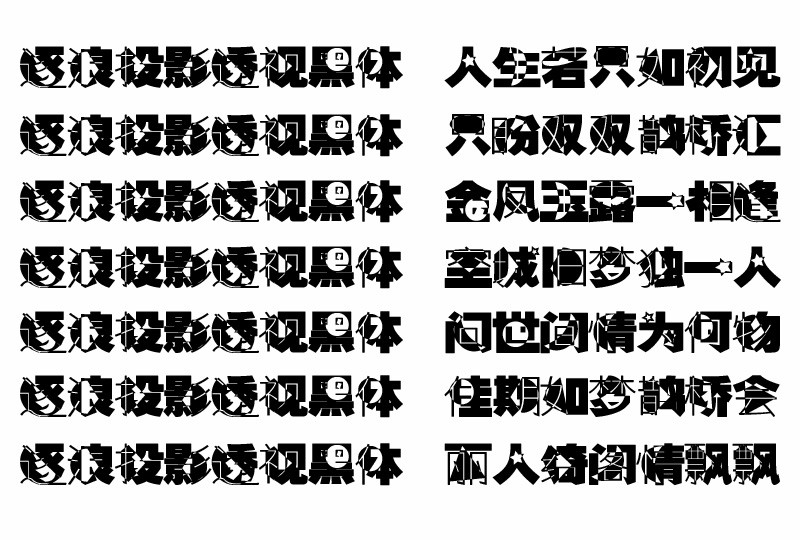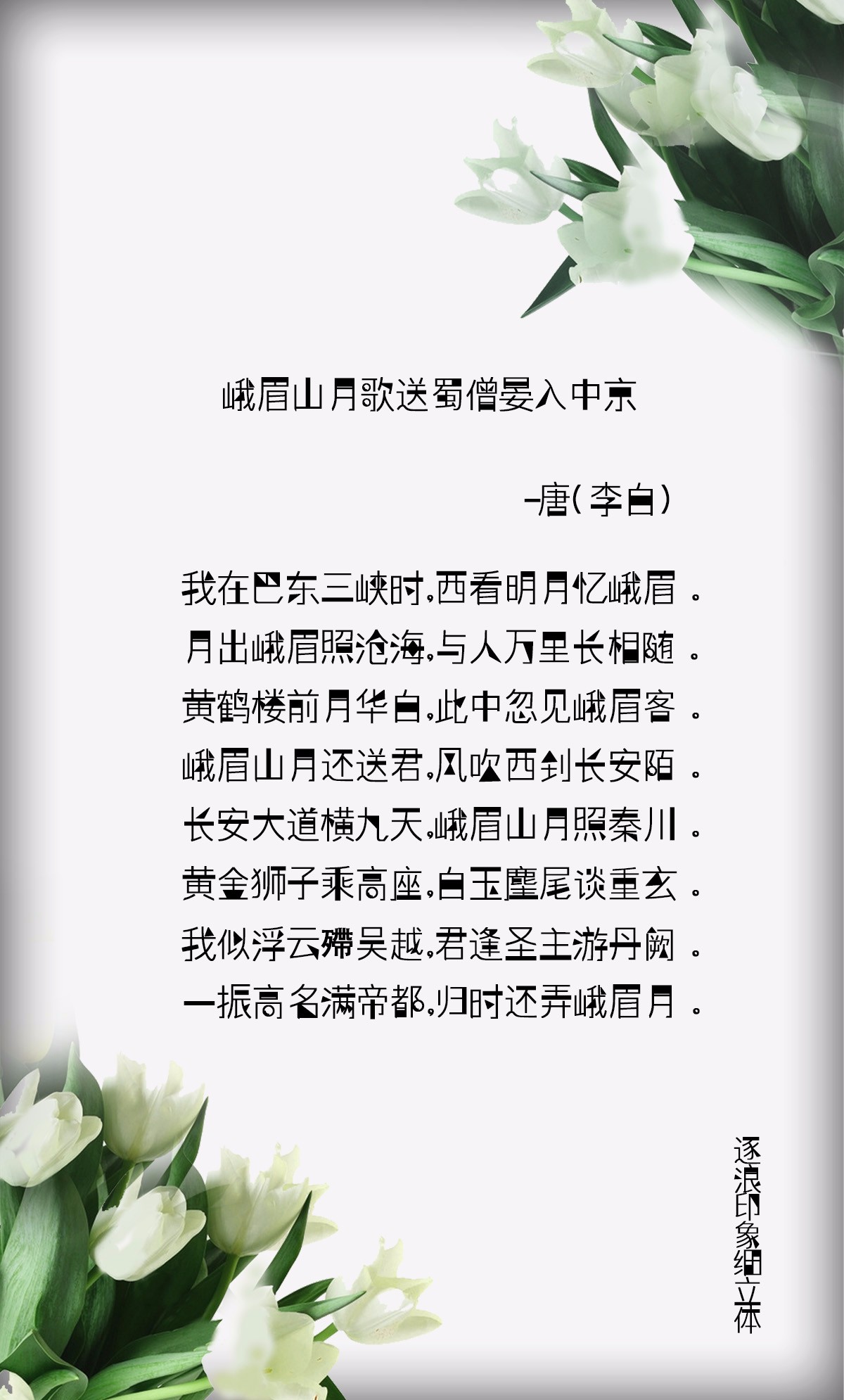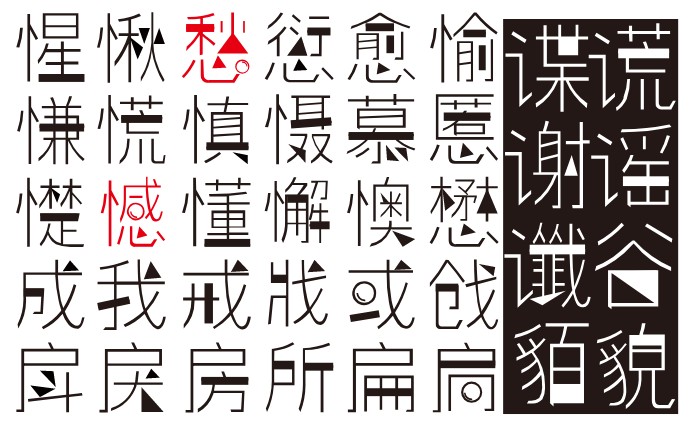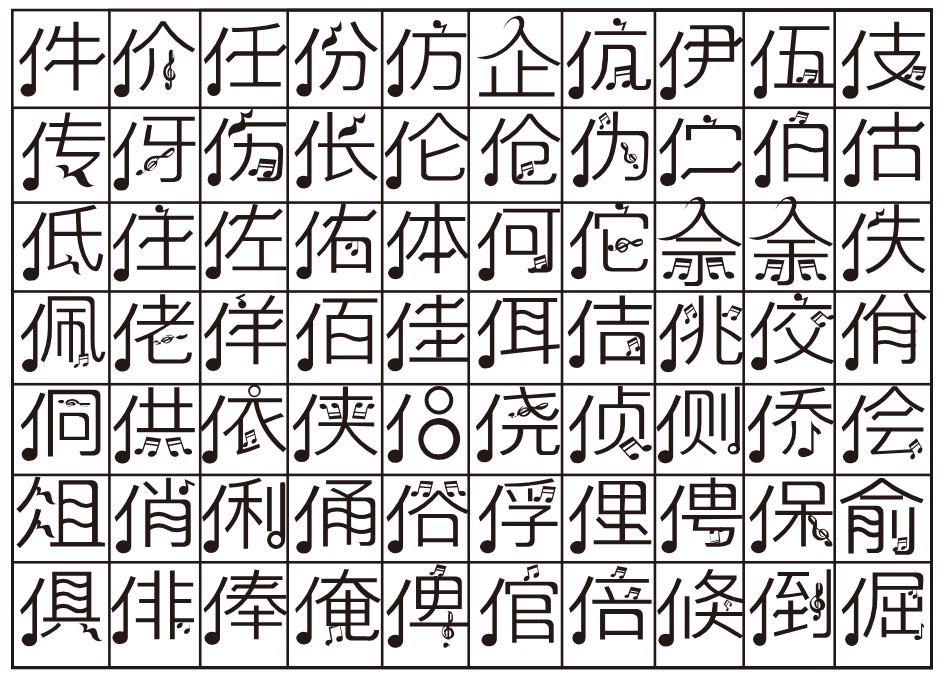
大美汉字-逐浪字库发布2018度中期作品
2018年5月,逐浪字库迎来了新的一期字体更新,这次的产品结合了多方面发效应,此次字体的更新也是相当迅速的,对于开发者及字体设计爱好者来说的话,已经是等待的有点迫不及待了,这次更新的字体是有着根据现代人与结合古代人对字体这块的认知来更新的,为了能做设计出这次的字体,也是经过了多方面的更新与设计,本次逐浪字库发布的四款字体分别为:逐浪投影透视黑体、逐浪印象细立体、逐浪帅宋斜楷体、逐浪音乐符号歌谱体。
针对于这次的更新我们的字库设计部分也是用了很大的准备来创作的,空间跨度很大,其中逐浪印象细立体这款字体的立体主义(Cubism)是西方现代艺术史上的一个运动和流派,又译为立方主义,1908年始于法国。立体主义的艺术家追求碎裂、解析、重新组合的形式,形成分离的画面,以许多组合的碎片型态为艺术家们所要展现的目标。艺术家以许多的角度来描写对象物,将其置于同一个画面之中,以此来表达对象物最为完整的形象。
逐浪字库的团队成员,以印象主义切入,创造了独到的字库体验。
它如三角台灯,照亮下面的丽人、生活与家。如字:流、琦
它如远方的山,又如父爱如山,在字的中间形成重心,如字:离
它是实验室的小烧瓶,俏皮的液体在不断上升-如字:潮。
它是方正厚实的几何之美,值得信任-如字:屋。
它有着红黑与、方与圆的对比-如字:蹦。
它向不规划挑战-如字:依、新、柳
它能在压抑的类比中脱颖而出-如字:熙。
它比别人更加多姿多彩,却又无感累赘-如字:柳
它如同绅士,总是身边有丽人或是配合得体-如字:酥
它如同毕加索笔下的几何造型,虽然看似简单,却又别具风格。
看似堆砌,却又有几何之美。
将西方的几何美学与东方的立体造型结合,
创造出独特的美,
使书写的意境得到最大的化进升。
逐浪印象细立体欣赏:
说完了逐浪印象细立体,再来说说看我们的逐浪音乐符号歌谱体吧,这款字体唯一特色的一点是体现出了音乐的风格,特别像是有些做广告牌的,又或者是传媒公司都可以使用这款字体来一个logo或者是招牌的宣传,现在使用特色字体来做广告牌的很多,如一些餐饮店、化妆店、服装店、酒店……等等。
逐浪音乐符号歌谱体,整款字的书写都处于非常舒适轻松的状态,设计中笔画时而饱满而结实有力,时而顽皮随性,音符的处理方式稚拙天真,字面饱满,给人带来一种欣赏音乐的温柔感和亲切感。